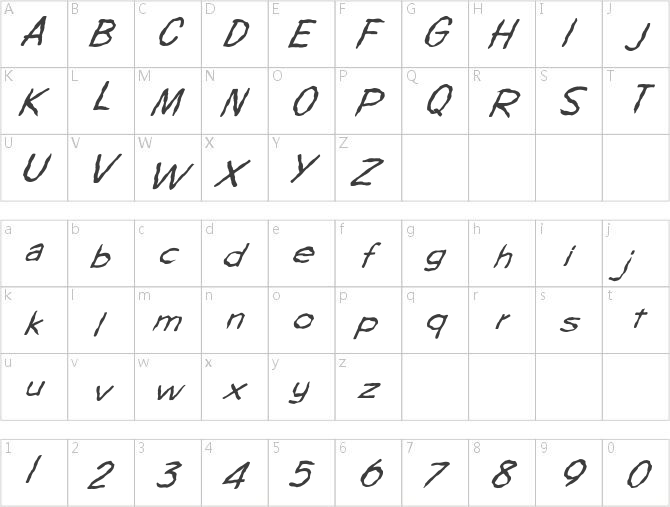
FZ HAND 7 WAVEY ITALIC
FZ HAND 7 WAVEY ITALIC介紹
FZ HAND 7 WAVEY ITALIC字體字庫是一款讓人賞心悅目、百看不厭的英文字體,適合各類廣告和產品包裝設計應用,字體大小0.07MB,格式為ttf字體,上傳用戶是曉語無聲,作者/版權方為未知